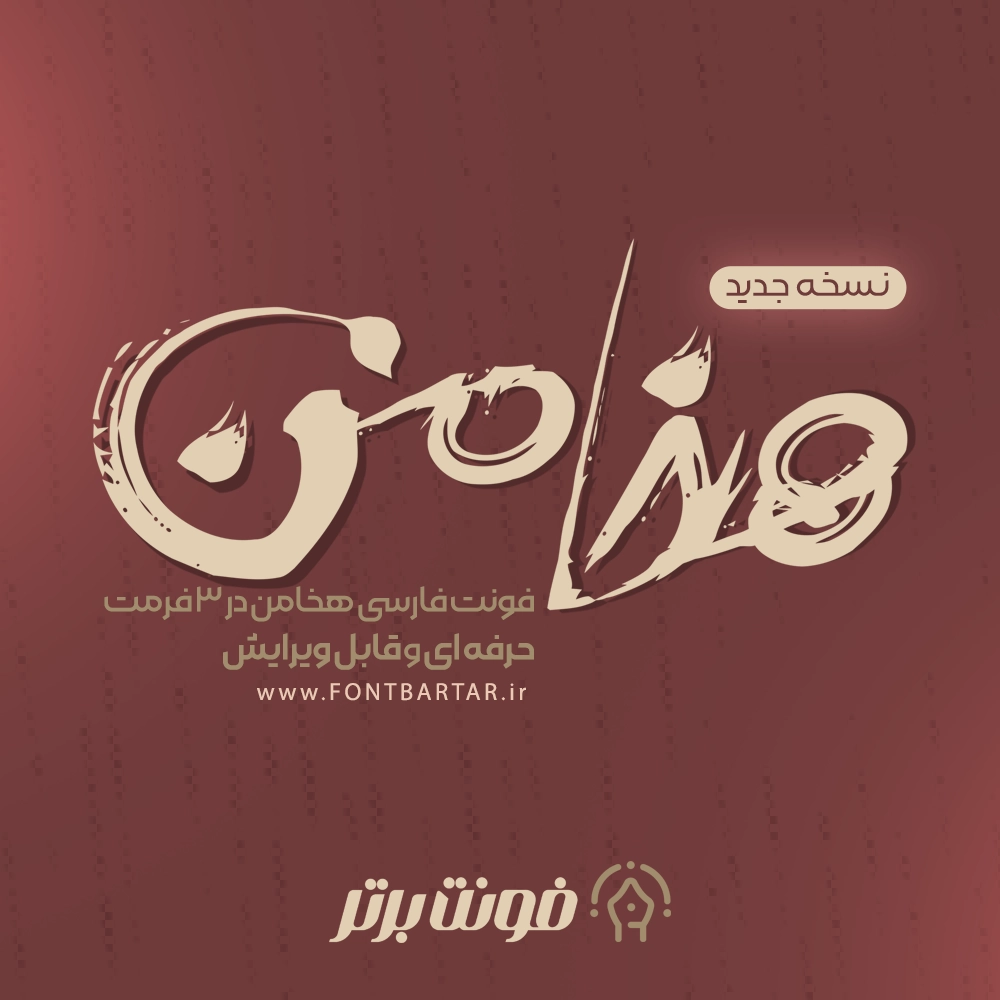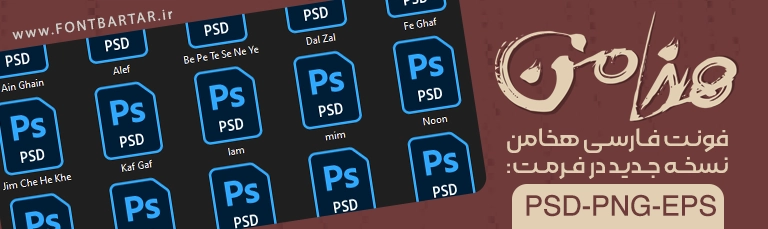
فونت خاص هخامن یکی از جذابترین و خلاقانهترین فونتهای لوگوتایپی فارسی است که با الهام از حس و حال باستانی، قدرت بصری بالا و خطوط متفاوت طراحی شده است. این فونت خاص فارسی برای طراحانی ساخته شده که میخواهند لوگوتایپهای یونیک، دستساز و چشمگیر خلق کنند؛ لوگوتایپی که حس اصالت، هنر و خلاقیت را در اولین نگاه منتقل میکند.
نسخه جدید فونت هخامن در سه فرمت حرفهای ارائه شده و کاملاً مناسب برای طراحی لوگوتایپ، تایپوگرافی، پوستر، کاور، برندینگ و انواع پروژههای گرافیکی است.
فونت هخامن یکی دیگر از فونت های طراحی لوگوتایپ و تایپوگرافی می باشد، فونت فارسی هخامن با طراحی حرفه ای و انعطاف پذیر می باشد و این امکان را فراهم می آورد که به راحتی بتوانید حروف را در کنار هم قرار دهید، با خرید فونت فارسی هخامن می توانید بدون هیچگونه دانشی لوگو تایپ طراحی کرده و تایپوگرافی های زیبایی انجام دهید و از آن کسب درآمد کنید.
فونت هخامن بر خلاف سایر فونت ها به صورت لایه باز بوده (psd) و امکان تایپ مستقیم در نرم افزار ها را ندارد همچنین شامل تمامی حروف از الف تا ی می شود این فونت به چینش های مختلف می تواند در کمترین زمان این امکان را به طراح بدهد که یک لوگو تایپ حرفه ای برای کسب و کار های مختلف طراحی کند ویژگی های این فونت حرفه ای را باهم مرور کنیم.
مزایای استفاده از فونت فارسی هخامن :
- تمامی حروف به صورت لایه باز
- ویرایش آسان حروف
- طراحی لوگوتایپ
- طراحی لوگو به صورت آسان و بدون هیچگونه آموزش
- شامل تمامی حروف از الف تا ی در تمامی حالت ها
ویژگیهای فونت لوگوتایپ هخامن
- طراحی دستساز و متفاوت با خطهای شکسته و چاپی
- نسخه جدید با کیفیت بهبود یافته
- مناسب برای لوگوتایپ و عنوانهای خاص
- کاملاً قابل ویرایش در نرمافزارهای گرافیکی
- مناسب پوستر، کاور، طراحی جلد کتاب، بنر و موشن
- قابلیت استفاده در فضای وب، چاپی و دیجیتال
- حس هنری، اصالت و قدرت بصری بالا
فونت خاص جدید از لحاظ ساختار و ریتم نوشتاری با هدف ایجاد برجستگی و جذابیت تایپوگرافیک طراحی شده و بهراحتی در انواع سبکهای گرافیکی قابل استفاده است.
این فونت برای لوگوتایپ، تایپوگرافی، پوستر، کاور و هر نوع طراحی خلاقانه و هنری بهترین گزینه است.